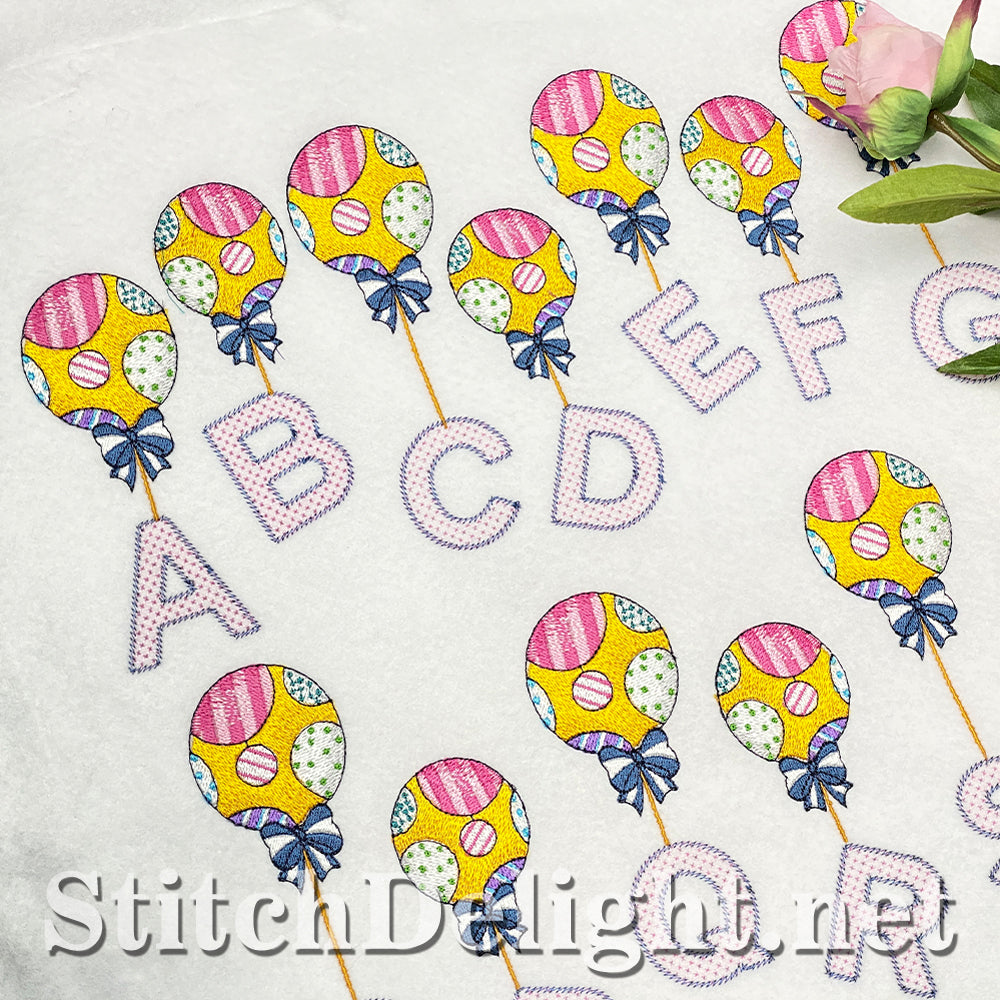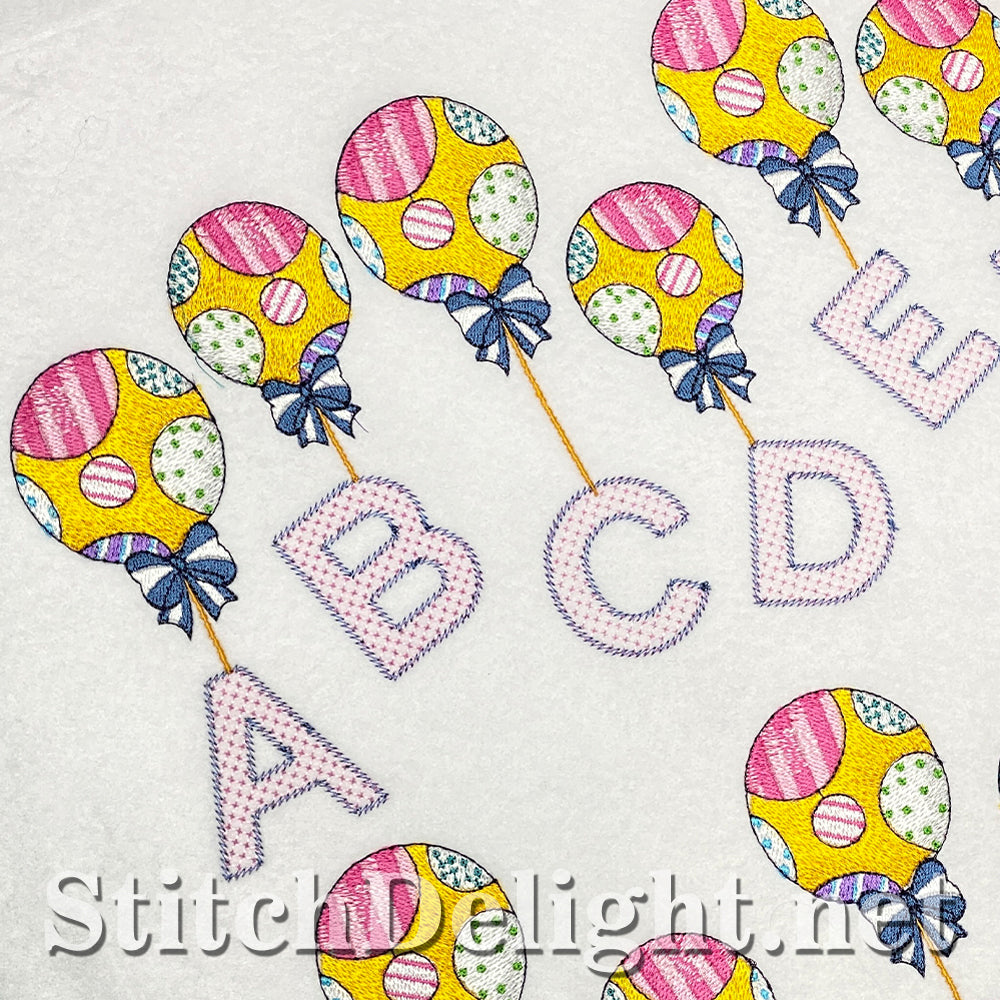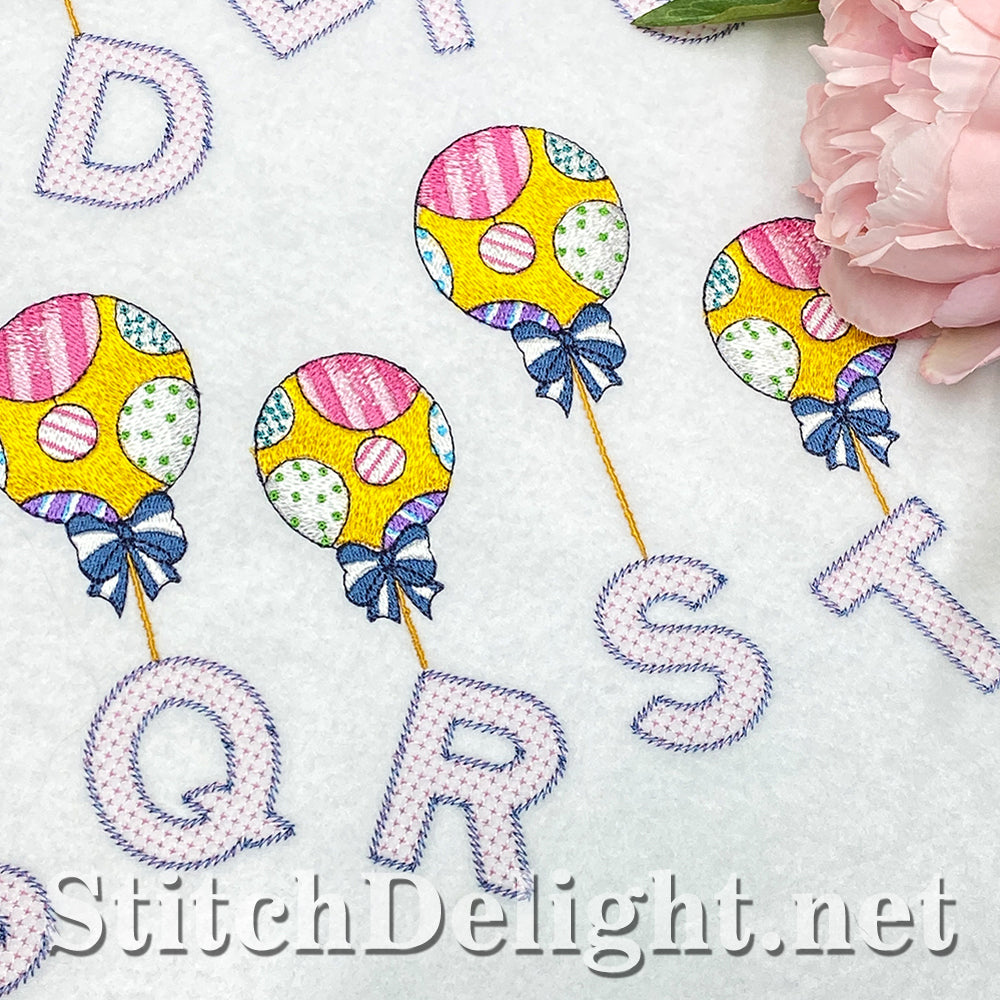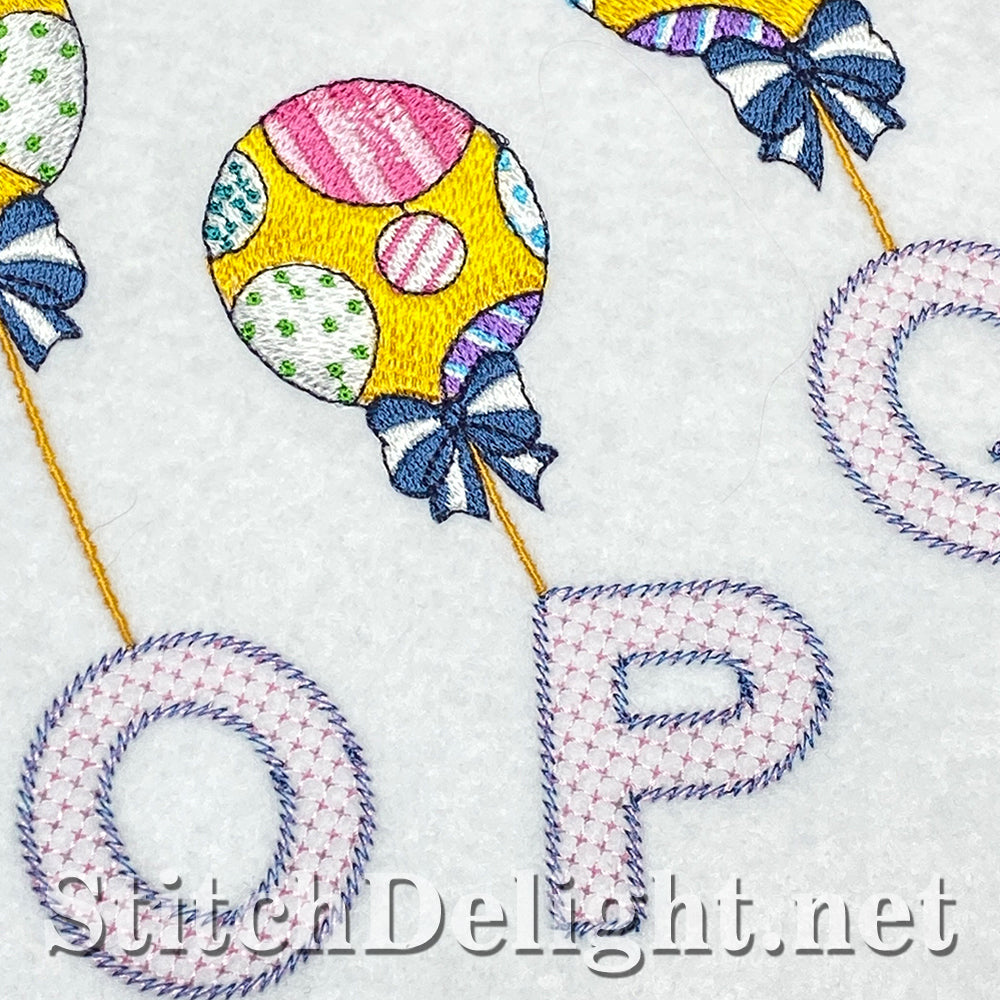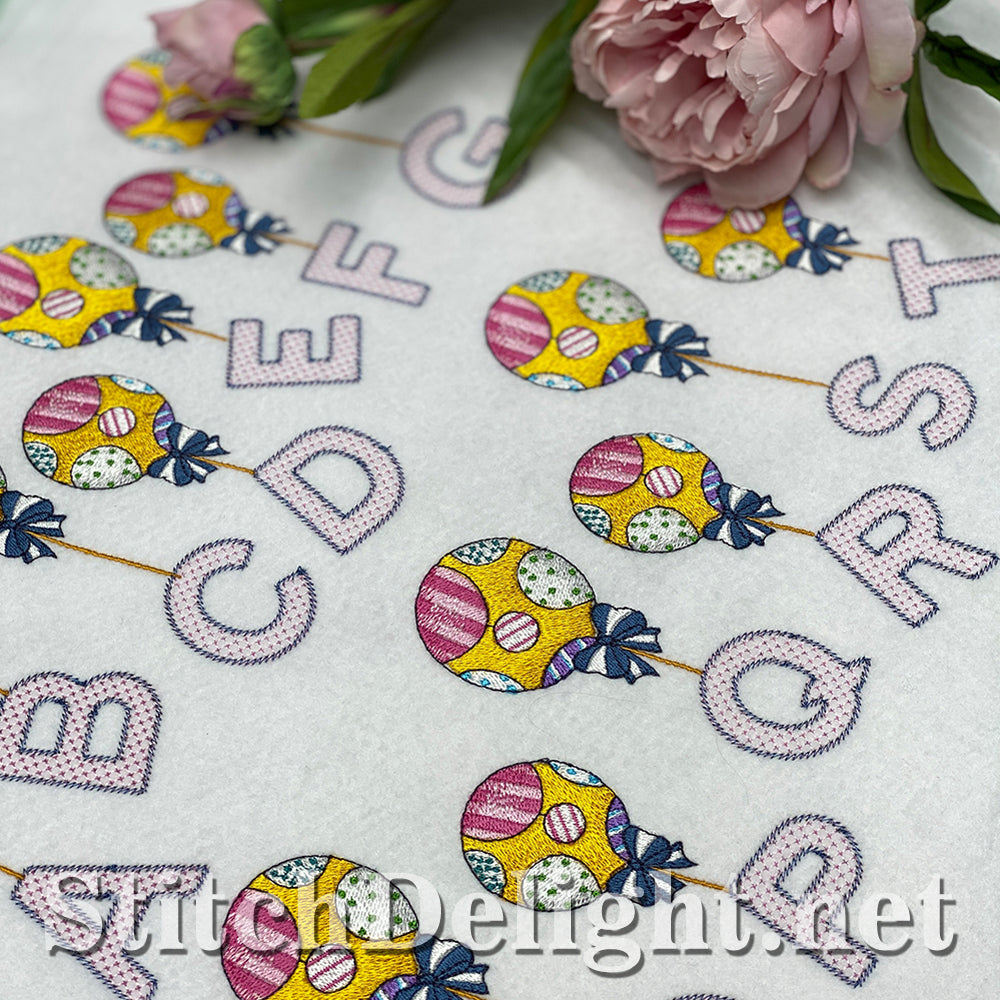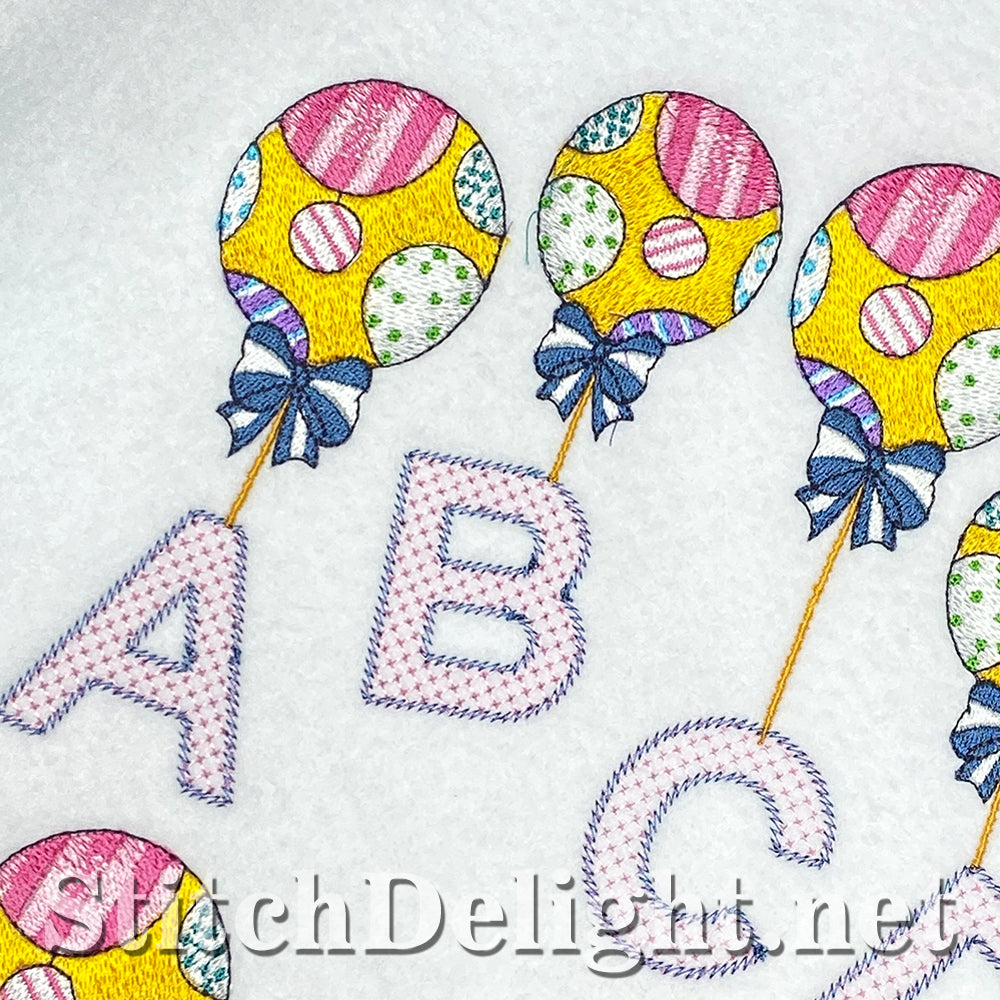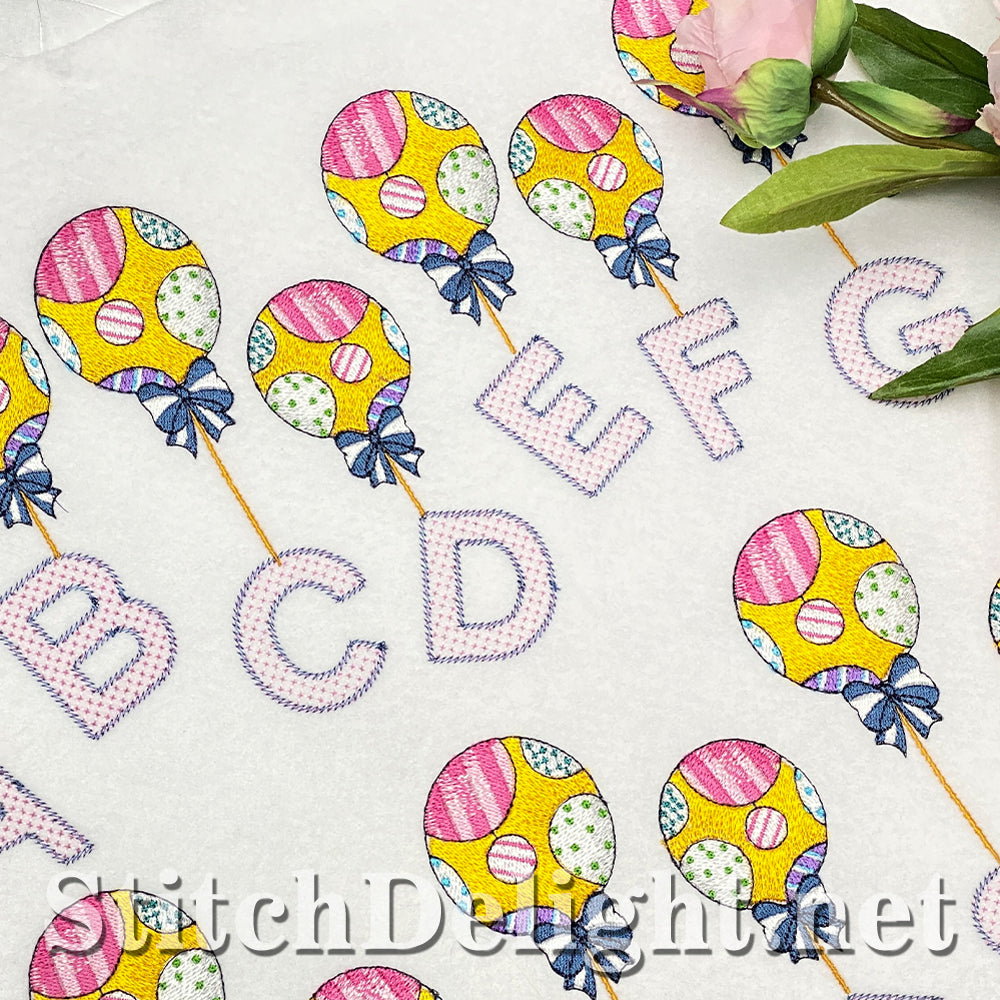
Cette police ne manquera pas de faire ressortir l'ambiance festive de tout cadeau ou vêtement sur lequel elle est cousue. Peut être utilisé dans de nombreux projets, des événements d'anniversaire à la décoration de la chambre de bébé, des serviettes, des débarbouillettes et même du linge. Le ciel est la limite avec celui-ci. La police a une hauteur moyenne de 5 pouces, elle est donc conçue pour le cerceau de 5x7".